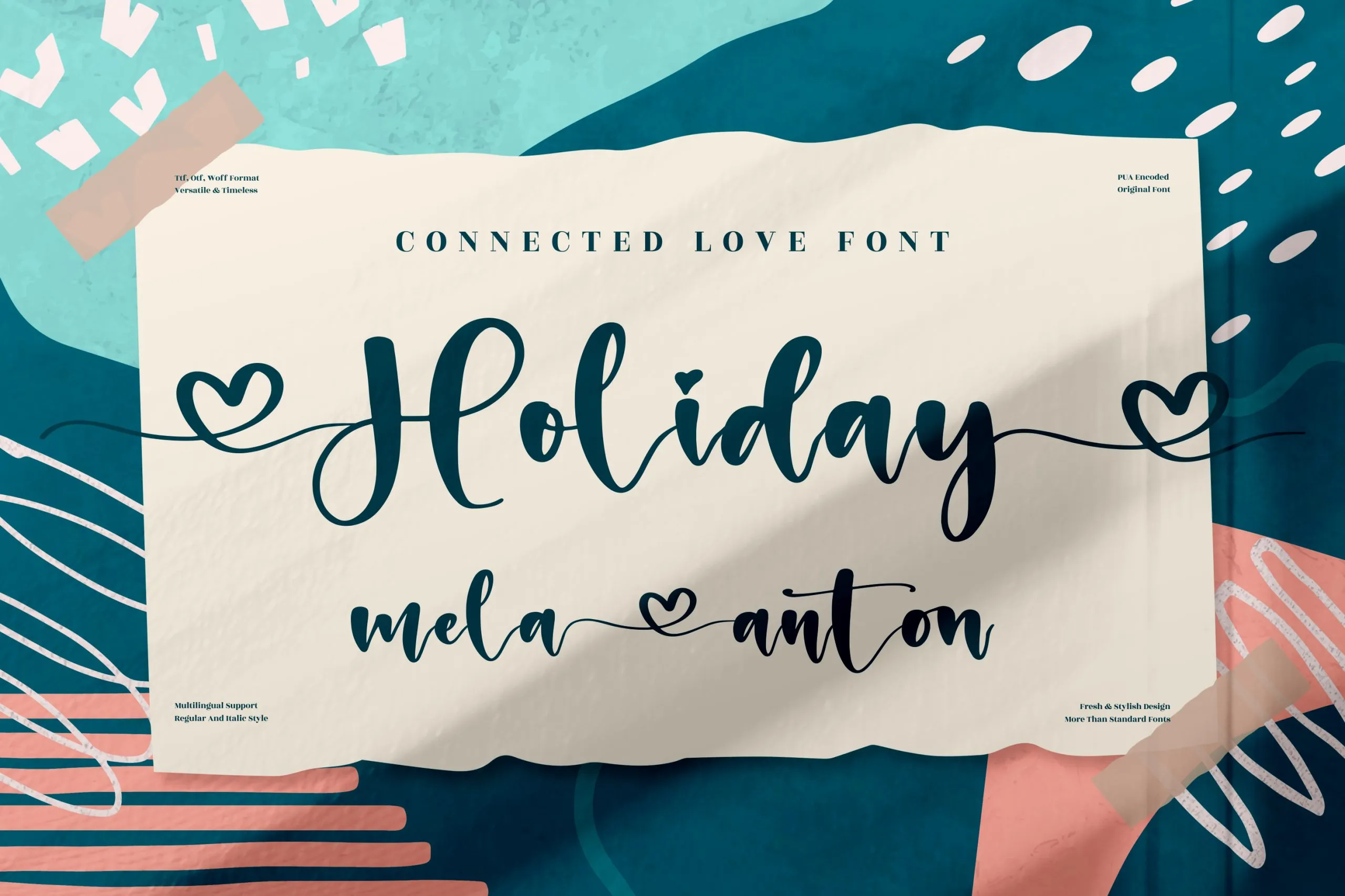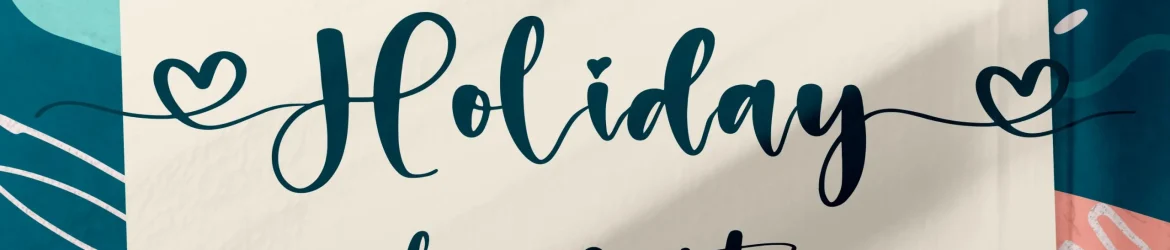
Holiday Calligraphy Font – Download Grátis
Este é um belo conjunto de tipografia calligrafia ideal para qualquer projeto. É perfeito tanto para logos e projetos de marca quanto para designs de móveis de casa, embalagens de produtos, xícaras, frases, quadros, cartões de nome, cartões de convite, cartões de agradecimento, etiquetas, fotografias, marcas d’água e até eventos especiais. Com esta fonte de calligrafia, você pode trazer um toque romântico a todas as suas criações que necessitam de uma escrita elegante. Esta fonte é perfeita para aqueles momentos especiais, tornando seus projetos ainda mais bonitos e memoráveis. Não importa o tipo de projeto ou evento em que você esteja trabalhando, a perspectype’s Calligraphy Font lhe oferece um toque especial que vai tornar sua obra ainda mais única.